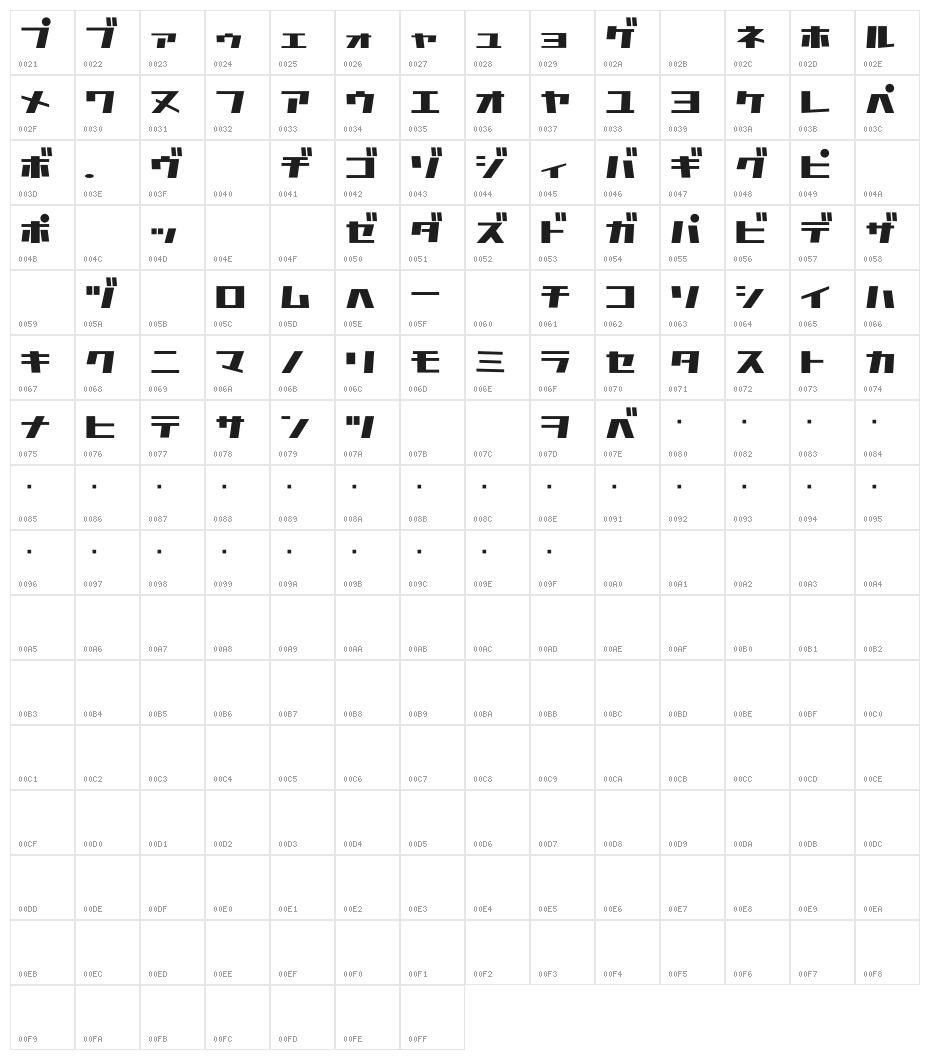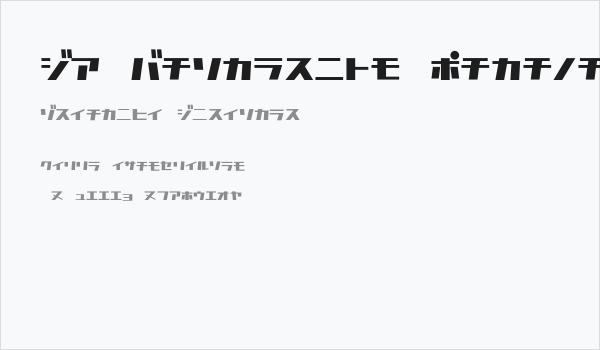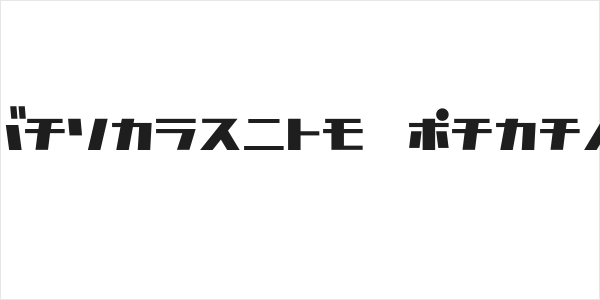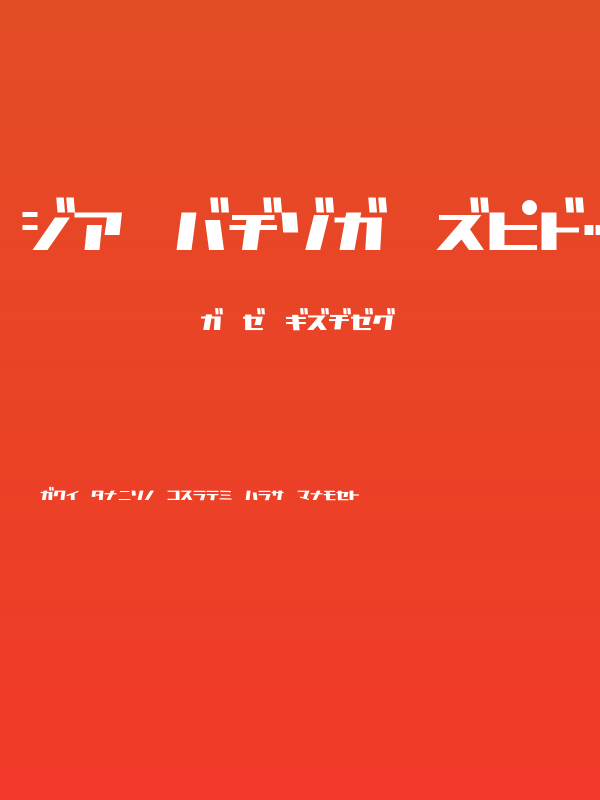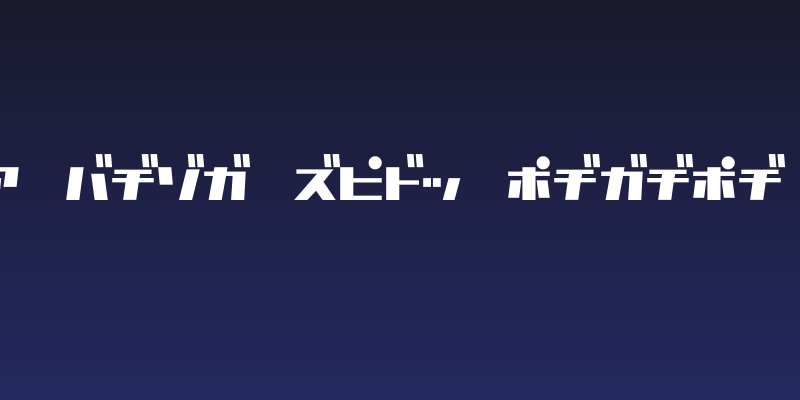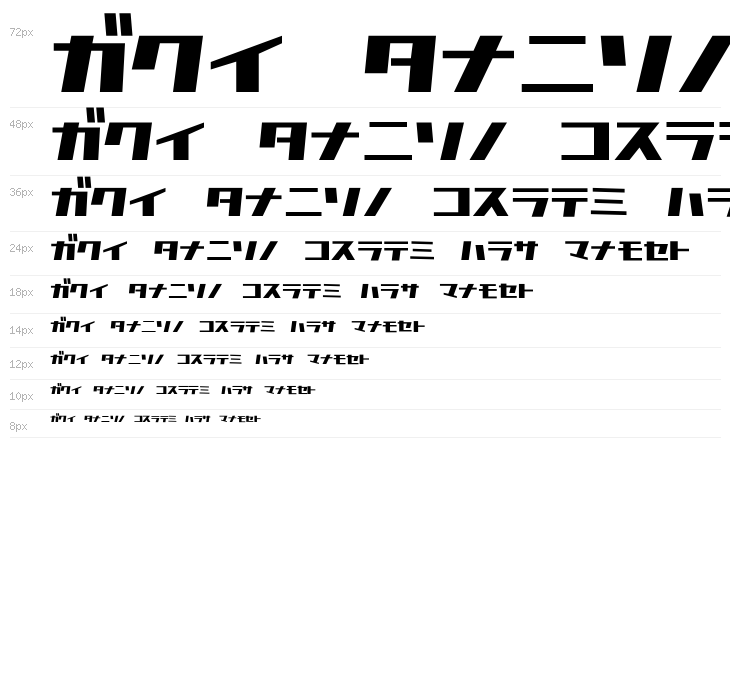
D3 Factorism Katakana Font
| 宽度 | Expanded |
| 整体风格 | Futuristic |
| 推荐项目 | Ideal for tech branding, sci-fi themed posters, video game titles, and modern advertising campaigns. |